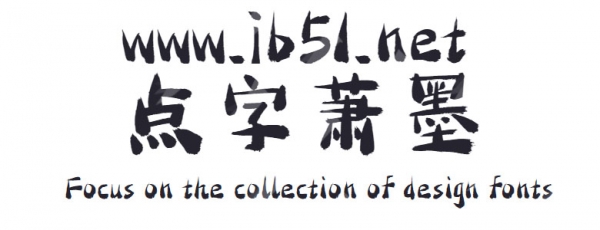
點(diǎn)字蕭墨體是由點(diǎn)字庫推出的藝術(shù)字體,字體筆畫取竹形態(tài),用筆靈活不拖沓,結(jié)字有行書之逸,適合應(yīng)用于藝術(shù)設(shè)計(jì)、各類廣告和產(chǎn)品包裝設(shè)計(jì)等領(lǐng)域。
筆畫取竹形態(tài),用筆靈活不拖沓,結(jié)字有行書之逸,又不失楷書雅正。整體清華其外、澹泊其中、清雅脫俗、不作媚世之態(tài)。